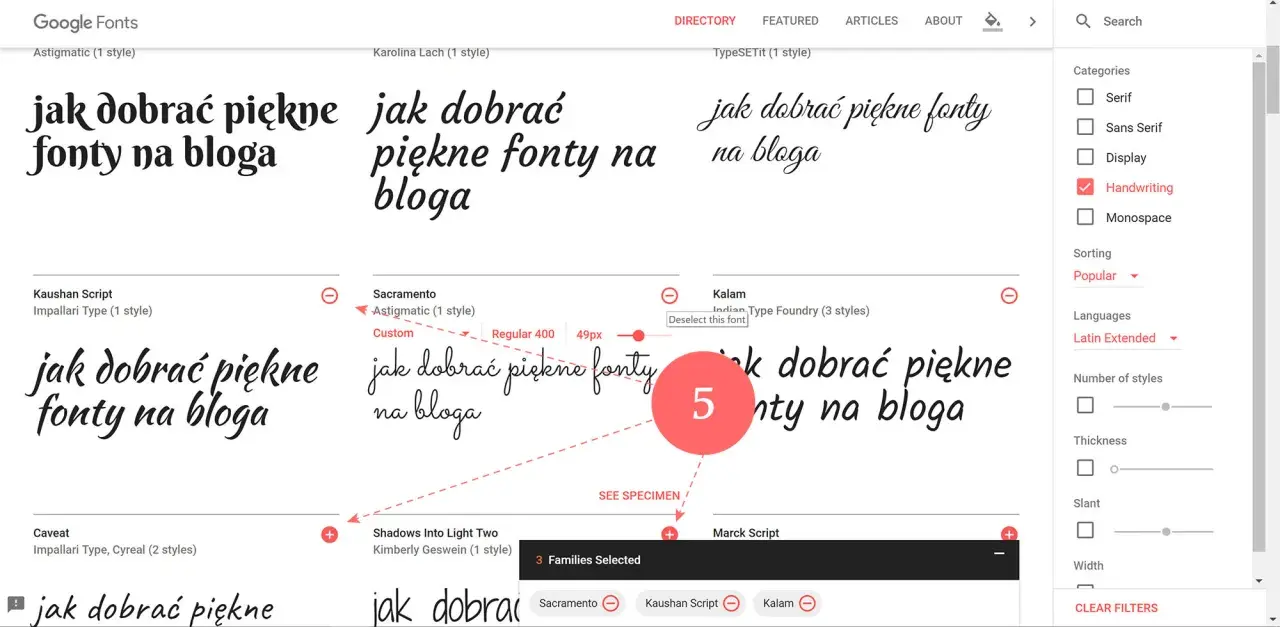
Typografia na stronie działa szybciej niż większość elementów wizualnych: albo buduje zaufanie, albo od razu je osłabia. W praktyce czcionki google najlepiej traktować jako narzędzie, a nie ozdobę, bo dobrze dobrany krój poprawia czytelność, porządkuje treść i wspiera sprzedaż w lokalnym biznesie. Poniżej pokazuję, jak rozumieć bibliotekę Google Fonts, jak ją wdrożyć i jak nie popełnić błędów, które psują efekt na telefonie i spowalniają stronę.
Najkrótsza droga do dobrej typografii to prosty wybór kroju, rozsądna liczba wag i poprawny fallback
- Na stronie usługowej zwykle wystarcza jedna rodzina fontów i 2 wagi, rzadziej 2 rodziny.
- Na stronach lokalnych firm najważniejsze są: czytelność, kontrast, szybkość i konsekwencja w całej witrynie.
Czym są Google Fonts i kiedy naprawdę pomagają stronie
Google Fonts to biblioteka krojów pisma udostępnianych do użytku w internecie, aplikacjach i materiałach graficznych. Według dokumentacji Google Fonts, fonty są open source i można je stosować także komercyjnie, więc barierą nie jest licencja, tylko rozsądne wdrożenie i dobór kroju do celu strony.
Największa zaleta tej biblioteki jest praktyczna: zamiast ręcznie hostować pliki i zarządzać wieloma wariantami, możesz pobrać gotowy styl i użyć go w CSS. To przyspiesza pracę, ale nie zwalnia z myślenia o typografii. Dobra czcionka na stronie lokalnego salonu, gabinetu czy firmy usługowej ma przede wszystkim ułatwiać kontakt z ofertą, cennikiem i numerem telefonu, a nie odwracać uwagę od treści.
Ja patrzę na to tak: jeśli krój nie poprawia czytelności albo nie wzmacnia charakteru marki, zwykle jest tylko dekoracją. A dekoracje mają sens dopiero wtedy, gdy nie utrudniają czytania. To prowadzi prosto do wyboru właściwego stylu i pary fontów, bo tu najłatwiej przesadzić.
Jak dobrać krój do marki i czytelności
Dobry wybór zaczyna się od pytania: co strona ma zrobić w 5 sekund? Jeśli ma sprzedać usługę, krój powinien być spokojny, stabilny i czytelny na małym ekranie. Jeśli ma budować bardziej premium wizerunek, można dodać odrobinę charakteru w nagłówkach, ale treść nadal musi zostać prosta do skanowania.
W lokalnym marketingu najczęściej wygrywa układ: jeden neutralny font do treści i drugi, bardziej wyrazisty, tylko do nagłówków albo wyróżnień. W praktyce to zwykle wystarcza. Trzy lub cztery rodziny na jednej stronie to już częsty sygnał chaosu, a nie kreatywności.
| Rodzaj kroju | Kiedy działa najlepiej | Co daje | Na co uważać |
|---|---|---|---|
| Sans-serif | Strony usługowe, landing page, kontakt, oferta | Nowoczesność, prostota, dobra czytelność na telefonie | Może wyjść zbyt neutralnie, jeśli nie ma wyraźnej hierarchii |
| Serif | Marki premium, kancelarie, treści eksperckie, editorial | Wrażenie autorytetu i elegancji | W małych rozmiarach nie każdy krój jest równie wygodny |
| Display | Same nagłówki, kampanie, krótkie hasła | Mocny charakter i wyróżnienie | Nie nadaje się do długich akapitów |
Przy wyborze sprawdzam też rzeczy bardzo przyziemne: czy font ma polskie znaki, czy nie myli się litera „l” z „I” i cyfrą „1”, oraz czy dobrze wygląda w 16-18 px. To brzmi banalnie, ale właśnie tu najczęściej przegrywają najbardziej efektowne projekty. Jeśli masz wątpliwość, postaw na prostszy krój i lepszą hierarchię, bo to daje pewniejszy efekt. Następny krok to wdrożenie bez niepotrzebnego obciążania kodu.
Jak wdrożyć font bez komplikowania kodu
Google Fonts można podłączyć bardzo szybko, ale warto zrobić to świadomie. Obecny standard opiera się na arkuszu stylów i regułach CSS, a nie na przypadkowym kopiowaniu wszystkiego, co akurat pokazuje podgląd w bibliotece. Najprostszy schemat wygląda tak:
W praktyce liczą się trzy rzeczy:
-
Podlinkowanie arkusza stylów w sekcji
. -
Ustawienie
font-familyz zapasowym krojem, na przykładsans-seriflubserif. - Ograniczenie wag do tych, których faktycznie używasz, zwykle 400 i 700 albo jeden krój zmienny.
Jeśli korzystasz z nowszego API CSS2, możesz precyzyjniej wskazać warianty i zakresy wag. To ważne, bo Google Fonts obsługuje fonty zmienne i nie musisz pobierać osobnego pliku dla każdej odmiany. W wielu rodzinach jeden plik obejmuje szeroki zakres stylów, co daje większą elastyczność przy mniejszym narzucie technicznym.
Dokumentacja Google Fonts podaje też prostą zasadę: jeśli font ma służyć tylko do krótkiego napisu, nagłówka albo logotypu, można użyć parametru text=, żeby pobrać tylko potrzebne znaki. W niektórych przypadkach zmniejsza to rozmiar pliku nawet o 90%, więc to jedna z tych drobnych zmian, które realnie robią różnicę. Po wdrożeniu trzeba jeszcze pilnować szybkości, bo tu najłatwiej niechcący zepsuć cały efekt.
Jak przyspieszyć ładowanie i uniknąć problemów na mobilnych stronach
Najczęstszy błąd nie polega na złym wyborze fontu, tylko na nadmiarze: zbyt wiele rodzin, zbyt wiele wag, zbyt ciężkie nagłówki i brak myślenia o telefonie. Strona lokalnej firmy nie potrzebuje zwykle rozbudowanego systemu typograficznego. Potrzebuje strony, która otworzy się szybko i od razu pokaże ofertę.
Warto pamiętać, że przeglądarka najpierw pobiera styl, a potem plik fontu. To oznacza, że przy słabym łączu albo wolniejszym urządzeniu może pojawić się krótkie przejściowe zachowanie tekstu, zanim font się ustabilizuje. Z tego powodu bezpieczny fallback w font-family to nie formalność, tylko zabezpieczenie UX.
| Sposób użycia | Kiedy wybrać | Plusy | Minusy |
|---|---|---|---|
| Proste podłączenie przez arkusz stylów | Większość stron firmowych | Najszybszy start, mało konfiguracji | Mniej kontroli nad detalami |
| Precyzyjne zapytanie CSS2 | Gdy ważna jest wydajność i konkretne warianty | Mniejszy transfer, lepsze dopasowanie wag | Wymaga świadomego doboru stylów |
| Self-hosting | Gdy potrzebujesz pełnej kontroli nad zasobami | Większa kontrola nad cache i wdrożeniem | Więcej pracy, więcej utrzymania |
Jeśli zależy ci na maksymalnej kontroli lub specyficznych wymaganiach technicznych, self-hosting może być sensowny. Dla większości małych i średnich serwisów nie jest jednak obowiązkowy. Ja zwykle zaczynam od prostego wdrożenia, ograniczam wagi i sprawdzam wyniki w praktyce. Dopiero potem decyduję, czy potrzebna jest dodatkowa optymalizacja, czy problem leży gdzie indziej.
Najczęstsze błędy przy korzystaniu z krojów z biblioteki
W typografii najłatwiej popełnić błędy, które z osobna wyglądają niegroźnie, ale razem robią sporo szkody. Widziałem już strony, które miały dobry branding, a przez złą typografię wyglądały taniej, ciężej albo po prostu mniej wiarygodnie.
- Zbyt wiele fontów na jednej stronie, przez co całość traci spójność.
- Brak fallbacku, czyli brak zapasowego kroju w CSS.
- Używanie ozdobnego fontu do długich akapitów, co męczy wzrok.
- Za dużo wag i stylów, co niepotrzebnie zwiększa obciążenie strony.
- Ignorowanie polskich znaków i testów na realnych treściach.
- Brak testu mobilnego, mimo że to telefon zwykle jest głównym ekranem użytkownika.
Do tego dochodzi jeszcze jeden częsty problem: zbyt mała różnica między nagłówkiem a tekstem głównym. Jeśli H1, H2 i akapit wyglądają podobnie, użytkownik nie widzi struktury. A bez struktury nawet dobry tekst traci na czytelności. Dlatego typografia powinna wspierać hierarchię, a nie ją rozmywać.
Jak zbudować hierarchię typograficzną dla firmy lokalnej
Na stronie lokalnego biznesu typografia ma pomóc klientowi szybko odpowiedzieć na trzy pytania: co oferujesz, gdzie działasz i jak się z tobą skontaktować. To oznacza, że pierwszeństwo ma czytelność, dopiero potem styl. Ja najczęściej układam stronę tak, by najważniejsze elementy były widoczne bez wysiłku, a fonty wzmacniały ten porządek zamiast z nim walczyć.
Praktyczny układ wygląda zwykle tak:
- H1 jako jedno mocne zdanie, bez nadmiaru ozdobników.
- Treść w neutralnym kroju, w rozmiarze 16-18 px i z komfortowym interliniowaniem.
- CTA w tej samej rodzinie, ale w wyraźniejszej wadze.
- Cennik i dane kontaktowe maksymalnie proste wizualnie, bez eksperymentów.
- Wyróżnienia tylko tam, gdzie naprawdę skracają drogę do decyzji.
Co wdrożyć najpierw, jeśli chcesz poprawić wygląd strony już dziś
Gdybym miał doradzić jeden prosty plan działania, zacząłbym od odchudzenia typografii. Zostaw jedną rodzinę fontów albo maksymalnie dwie, ogranicz wagi do naprawdę potrzebnych i sprawdź, czy treść nadal jest czytelna na telefonie. Potem dopiero dopieszczaj detale, bo to kolejność ma tu znaczenie.
- Sprawdź, czy font obsługuje polskie znaki i dobrze wygląda w realnym tekście.
- Ustal jeden font do treści i ewentualnie drugi do nagłówków.
- Dodaj fallback w CSS, żeby strona nie traciła czytelności przy opóźnieniu ładowania.
Takie podejście daje lepszy efekt niż dokładanie kolejnych ozdobników. W przypadku stron lokalnych firm typografia ma sprzedawać prostotą, a nie zaskakiwać komplikacją. Jeśli zadbasz o czytelność, spójność i szybkość, Google Fonts staną się realnym wsparciem dla marki, a nie tylko estetycznym dodatkiem.